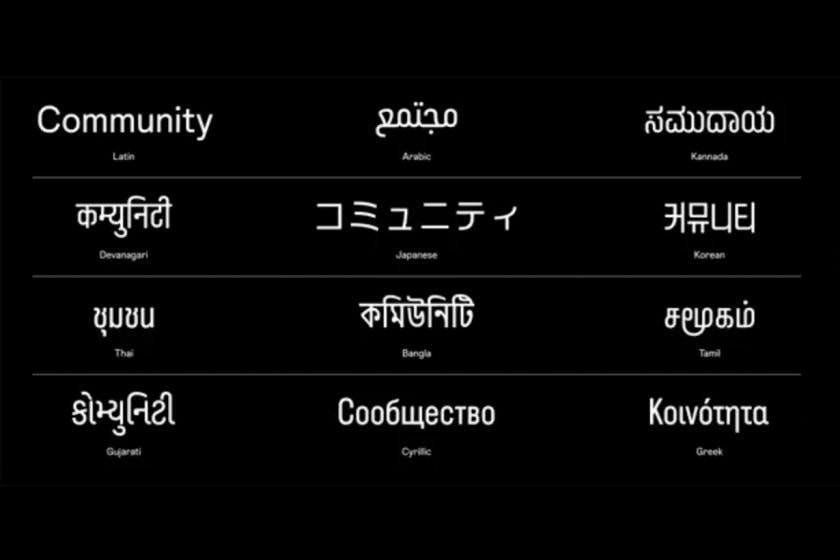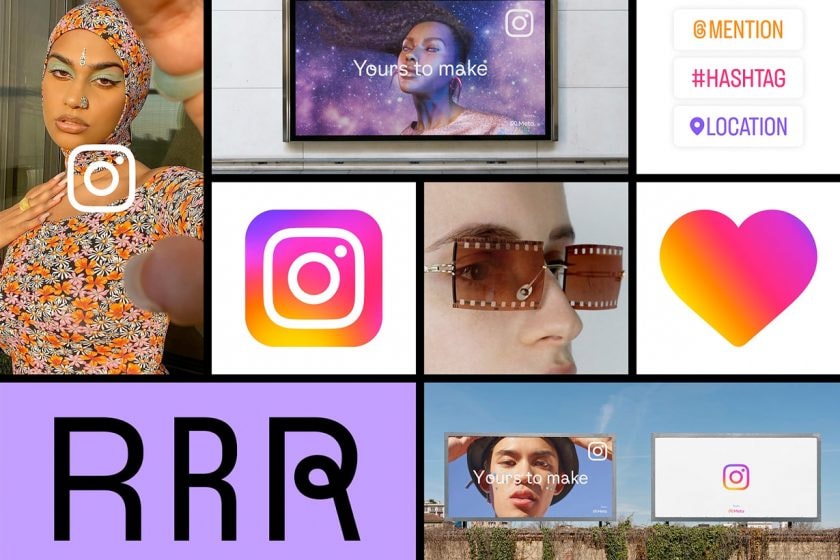
Instagram 3.0:即將迎來大改版!視覺形象、字體都會不一樣!
從復古的菲林相機 Logo 到現在的彩色版,還記得 2016 年一改版可是引起老粉絲一陣哀號,轉眼間六年也過去了,Instagram 這回宣布要替 App 改頭換面,Rebraning 的內容包括了配色、字體、Logo 等等細節。最令人好奇的全新視覺,根據外媒報導,會保留漸層的元素,並且打造 3D 的模組。而花費最多心思的還有全新字體,命名為 Instagram Sans,不只有英文,Instagram 請來語言學家,讓 Instagram Sans 這個字體可以完美從阿拉伯文、泰文、日文… 等世界上不同的語言展現,讓每一位不管是創作者、使用者可以打破語言的框架,好好享受在社群上的舞台。